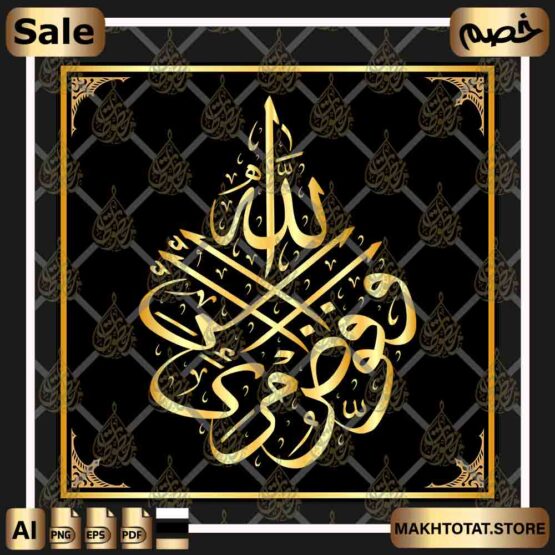
وأفوض أمرى إلى الله بخط الثلث Quran Calligraphy In Thuluth Font
“وأفوض أمري إلى الله”: رحلة إيمانية بِخطّ الثلث
مقدمة:
تُعدّ الآية الكريمة “وأفوض أمري إلى الله إن الله بصير بالعباد” من أشهر آيات القرآن الكريم، حيث تُعبّر عن التوكّل على الله سبحانه وتعالى، والتفويض إليه في كلّ أمرٍ. وقد حظيت هذه الآية باهتمام كبير من قبل الخطاطين عبر العصور، حيث كتبوها بخطوطٍ مختلفة، وكان لخطّ الثلث نصيبٌ كبيرٌ من هذه الكتابة.
خطّ الثلث:
يُعدّ خطّ الثلث من أقدم وأهمّ خطوط الكتابة العربية، ويتميز بجماله وقوته ووضوحه. نشأ هذا الخطّ في بلاد الشام في القرن الثاني الهجري، وانتشر بعد ذلك في جميع أنحاء العالم الإسلامي.